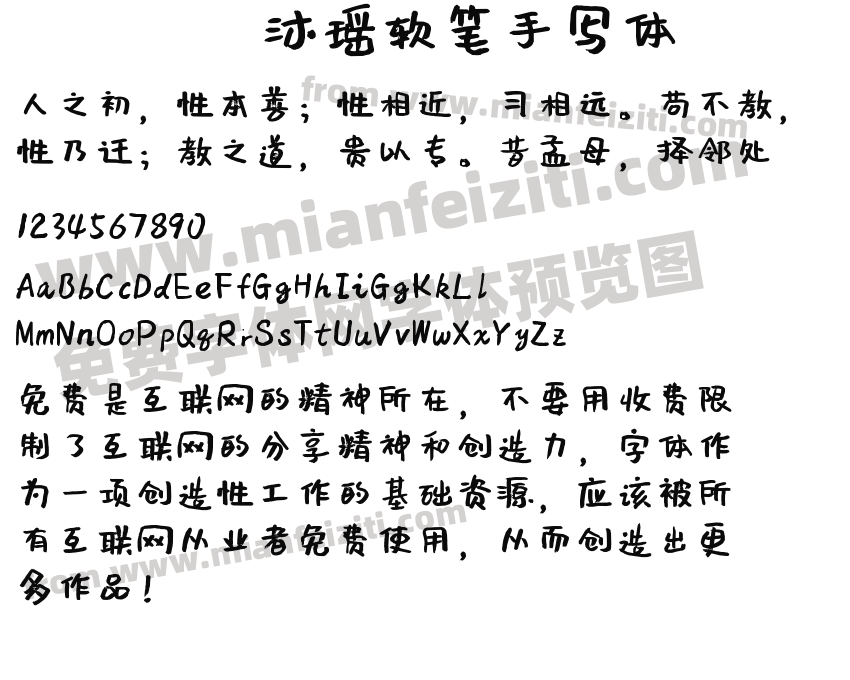
字体风格: 手写体
没有华丽的创作过程介绍,因为它的确是用笔写成,只有一个简单的故事,希望你能读一读。
我的成长经历中,没有刻意练过手写字。
不过,在手写海报方面倒是有一段经历。和现在的直接喷绘印刷不同,学生时代经常需要手写海报,经常一式多份。原本是需要用马克笔写POP字,但毕竟马克笔对于我的学生时代来说,价格很昂贵,于是大家都用排笔+广告色的方式进行创作。与传统的中文书法楷隶行草不同,这种书写方式可以把字写得较为可爱,也算是一种更加手写化的广告字体。
后来在创作漫画类作品的过程中,我发现这种字体也很适合用于休闲漫画、插画,于是在排笔书写的基础上逐渐变成了中性笔书写,并坚持了较长的时间,也逐步有了自己的书写风格。在从事平面设计的工作中,经常需要手写字,我发现楷隶行草之类的字体较多,较为休闲可爱的字体较少,好看的几款都有较为严格的版权限制,设计师使用时需要较高的门槛。
2019年5月,决定开工,匆匆在朋友圈立了FLAG,逼迫有拖延的自己去完成这个事情。
因为七月恰好是女儿周岁生日,就用女儿的名字拼音来命名,叫做“Muyao”,字母命名是方便兼容各类软件。因为是用软头毛笔写的,全名就叫做「沐瑶软笔手写体」。
我和妻子是因为写字认识的,也算是因字结缘。创作这套字体,也希望能结识更多的朋友,希望能够抛砖引玉,激发更多朋友能够创作大神级的作品。
于是,两个月,我“做”一款字体。
确切的说,是写一堆风格接近的字(GB2312标准的6763个汉字加数学英文字母和常用标点),凑成一套字体。
我知道,这也许是一件费力不讨好的事情,但是我依然认真去完成了。